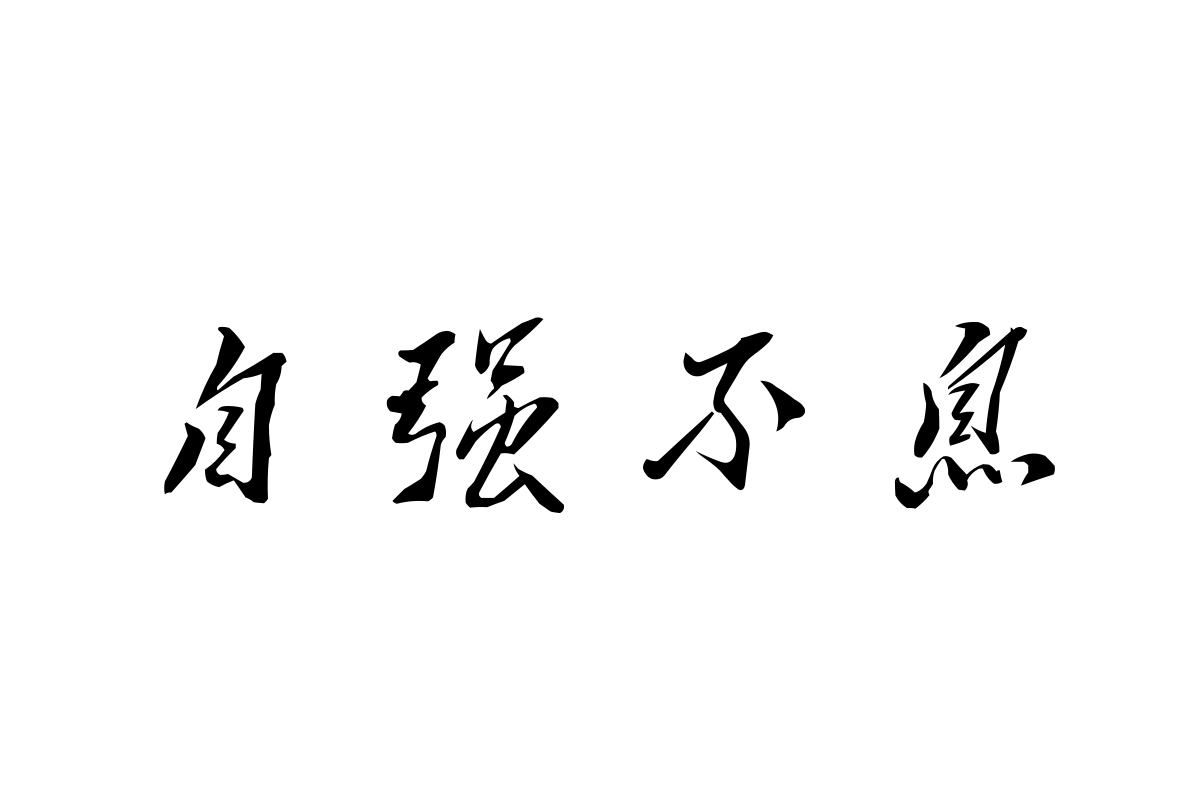
三极艺明书体是一款现代中文书法字体,由北京三极艺明文化传媒有限公司设计。这款字体具有独特的风格和特点,包括:
1. 线条流畅自然,笔画圆润饱满,给人一种优雅的感觉;
2. 字体结构紧凑,字形大小适中,易于阅读和书写;
3. 笔画粗细变化丰富,既有粗犷豪放的气势,又有细腻柔和的韵味;
4. 字形结构严谨,符合汉字书写规范,便于识别和记忆。
三极艺明书体适合用于各种场合,如广告宣传、企业标识、书籍封面等,能够展现出独特的艺术魅力和文化内涵。